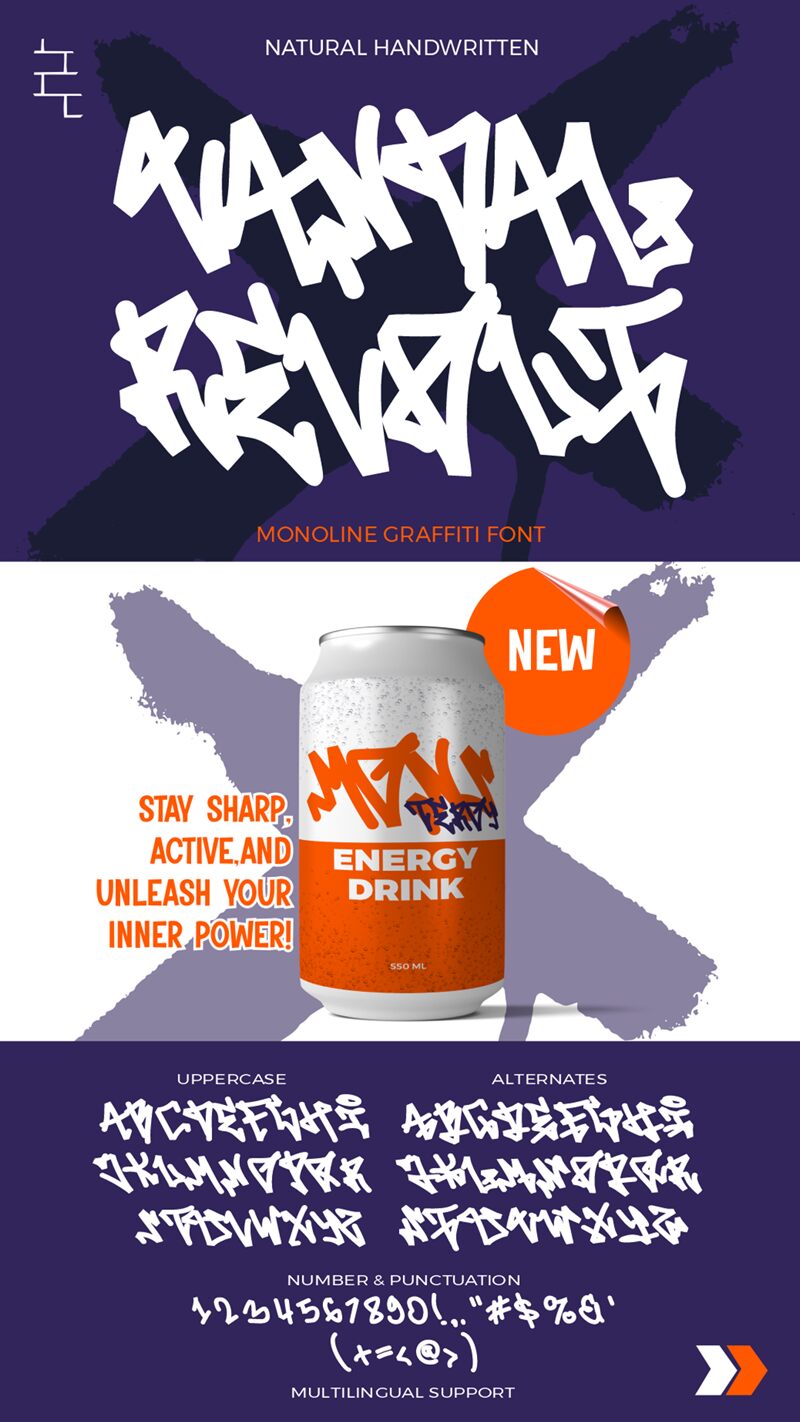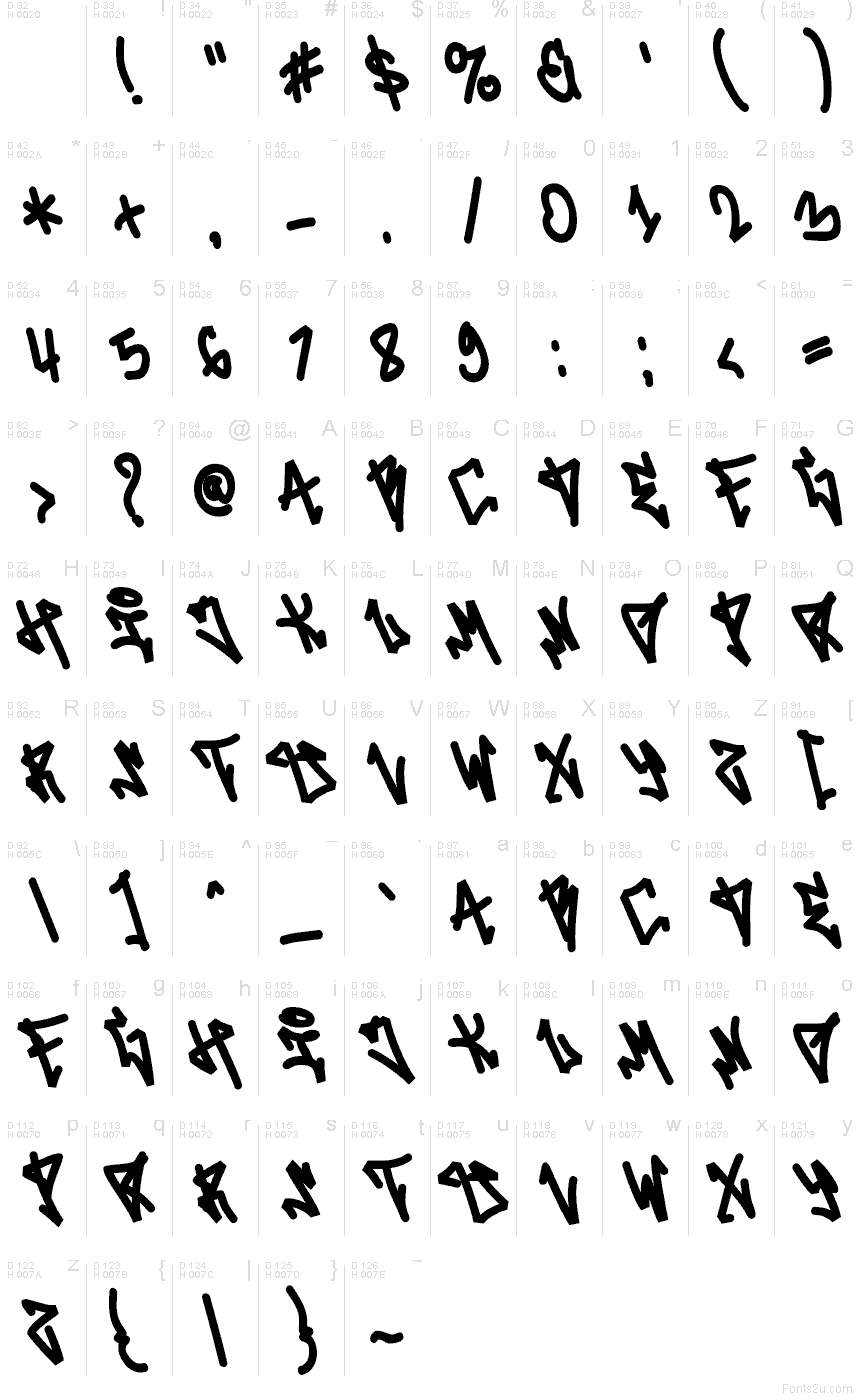
Písmo Vandal Revolt od Muhammada Panji Ramdhaniego (Sipanji x Figuree) je bezplatný font ve stylu graffiti, který má říz čerstvého inkoustu – je zubatý, rychlý a nekompromisně výrazný. Tahy působí ručně a neposedně, s ostrými úhly a těsným rozestupem, díky čemuž vypadají jako tag nahozený na zeď jedním dechem. Přináší okamžitou energii ulice bez potřeby dalších textur nebo efektů.
Vandal Revolt skvěle funguje na hudebních plakátech, brandingu skateboardových či streetwearových značek, obalech alb/mixtapes, miniaturách na YouTube, akčních letácích, sadách nálepek a úderných reklamách na sociálních sítích. Nechte ho vyniknout ve velké velikosti, aby chaotický rytmus zůstal čitelný, a nechte ho hrát hlavní roli na čistém pozadí. Tento bezplatný font doplňte obyčejným zúženým bezpatkovým písmem pro data, kredity nebo detaily produktů, aby si styl udržel svou pozici v popředí.